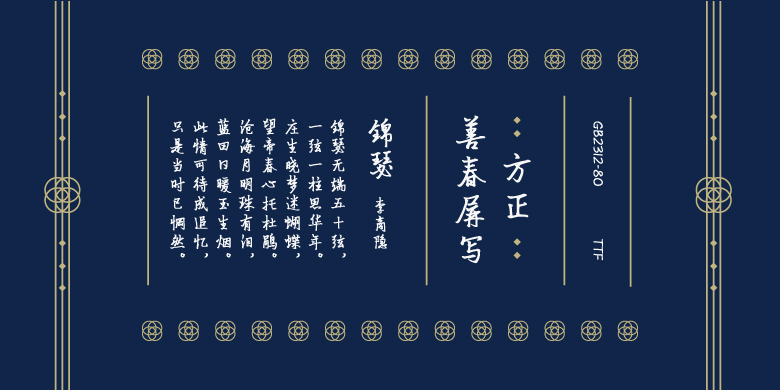
方正善春屏写
字体品牌: 方正手迹 设计师:孙善春 字体分类:行楷、行书、创意书写 字体属性:精品字 字符集:大陆简体(GB2312-80)、简繁扩展(GBK) 发布时间: 2018
作者:孙善春,艺名萧非,号“熊猫老师”。浙江大学德国哲学博士。现为中国美术学院教师,硕士研究生导师。
作者以屏为纸,以指为笔书就。这是力将书法的时空性带进字体的一个充满生机的探索。笔画柔韧老道,富有动势,结体和畅优美,气息儒雅。屏幕书写的文字经数字化转换后,笔画光洁而统一,数据量较小,其质感更彰显现代技术文明。而通过纸质书写再进行扫描的传统制作方式则难以达到这样的效果。需要特别指出的是,作者用了近5年的练习来掌握屏写技能,为在信息时代唤起人们对汉字审美关注,付诸可贵的行动。该字体适合于广告和网络应用,并能胜任个性化文本的排版。